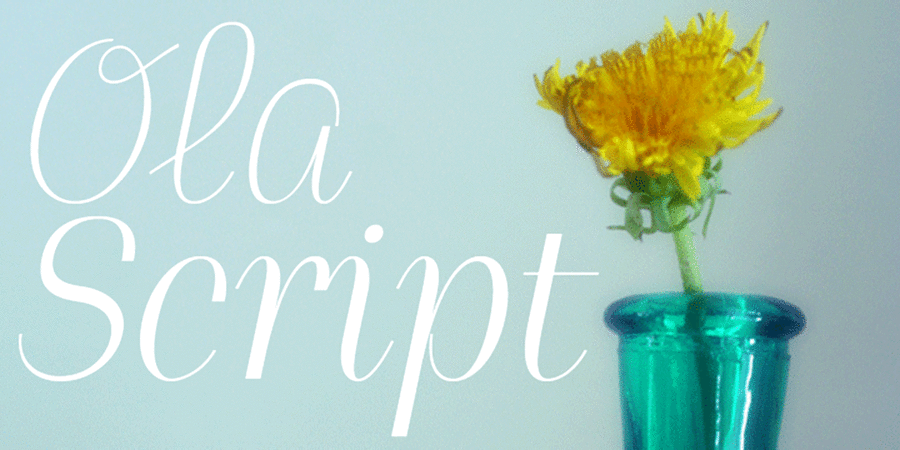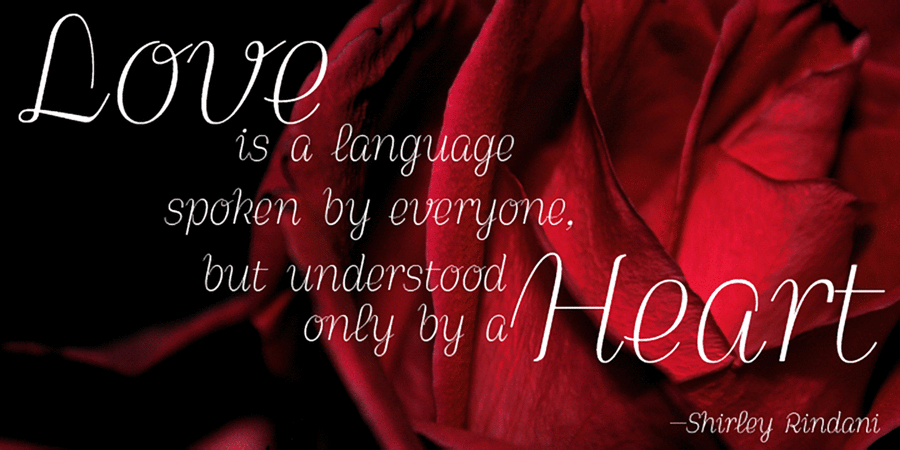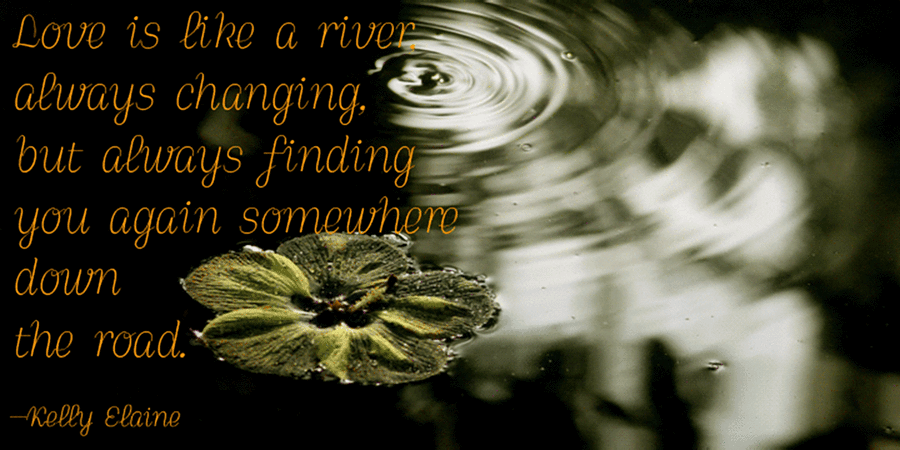
Ола скрипт – удивительно нежный и деликатный рукописный шрифт, идеально подходящий для поздравлений, приглашений и подарков. Имеет 2 начертания, отличающиеся по контрасту штрихов и поддерживает огромное количество языков. Разработан Сергеем Ткаченко в 2011 году.
Асоціації з сімейством шрифтів Ola Script 4FОсобистість і характер гарнітури:
делікатний, чистий, легкий, свіжий, тонкий, добрий, жіночний, казковий, наївний, милий, інтимний, крихкий, зелений, округлий, ніжний, музичний, ритмічний, акуратний, якісний, сентиментальний, поетичний, художній, чуттєвий, ввічливий, невагомий, прозорий, елегантний, весняний, повітряний, творчий, сексуальний, красивий, гарненький, симпатичний, рослинний, худий, дівчачий, святковий